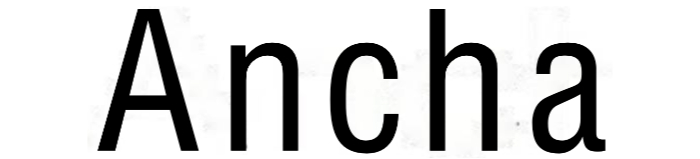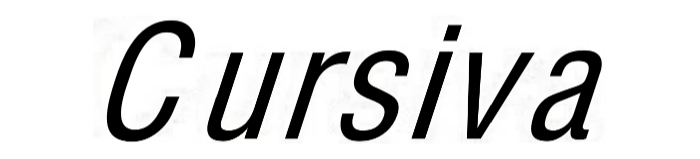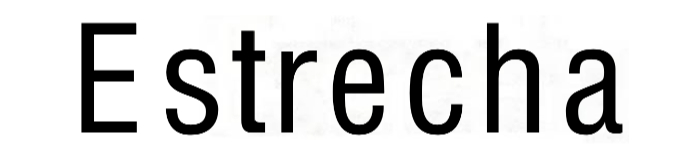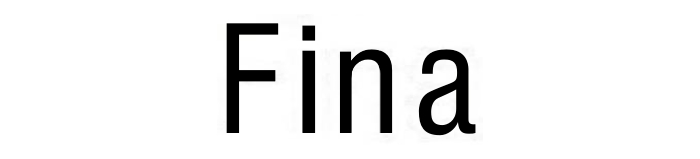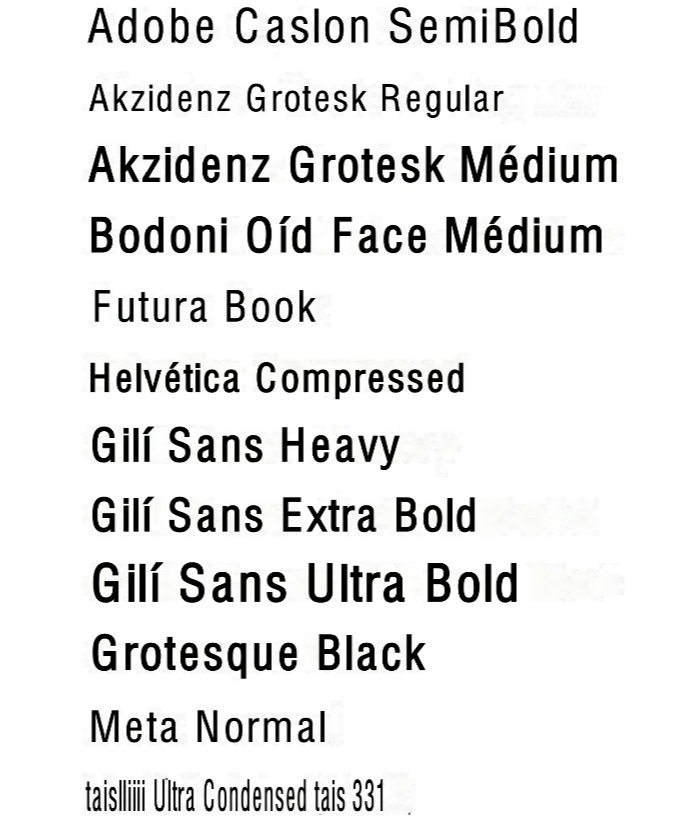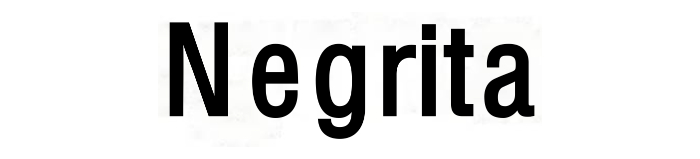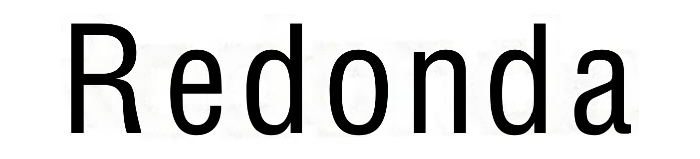
Cuando se conocen las partes de las letras, pueden identificarse los diferentes tipos con facilidad. Más allá de los rasgos característicos de un tipo, sin embargo, existen también aplicaciones de estilo que deberías reconocer. En una misma familia tipográfica pueden darse algunos de estos estilos, combinaciones de ellos o todos en su conjunto.
Redonda:
Es el estilo básico de las letras, y también se las denomina “romanas” porque las letras en caja alta derivan de las inscripciones en los monumentos romanos. Cuando se utiliza para describir el estilo de un tipo, el término “redonda" siempre hace referencia a la caja baja. En algunas tipografías existe un trazo ligeramente más fino que la redonda, que se denomina book.
Cursiva:
También llamada “itálica", nombre que procede de las escritura manuscrita italiana del siglo xv en la que se basan sus formas. (Véase "La Fuente" para una descripción de las letras oblicuas.)
Negrita:
Caracterizada por un trazo más grueso que la redonda, según las anchuras de trazo relativas que tenga un tipo puede denominarse seminegra, negra, extranegra o supernegra. En algunos tipos (en especial Bodoni), a la versión más negrita se le llama de cartel o “póster”.
Fina:
Tiene un trazo de menor grosor que la letra redonda. Las de trazos aún más delgados suelen denominarse superfinas.
Estrecha:
Tal como su nombre indica, es una versión estrecha de la letra redonda. Los estilos muy estrechos también suelen llamarse letras compactas.
Ancha:
Es exactamente lo que estás pensando: una variación expandida de la letra redonda.
La confusión de estilos dentro de las familias tipográficas puede resultar desalentadora para los principiantes; desde luego, sigue siendo una pequeña molestia incluso entre los diseñadores más experimentados. La única forma de manejar la profusión de nombres —como cuando se aprenden los verbos irregulares en francés— es aprendérselos de memoria.